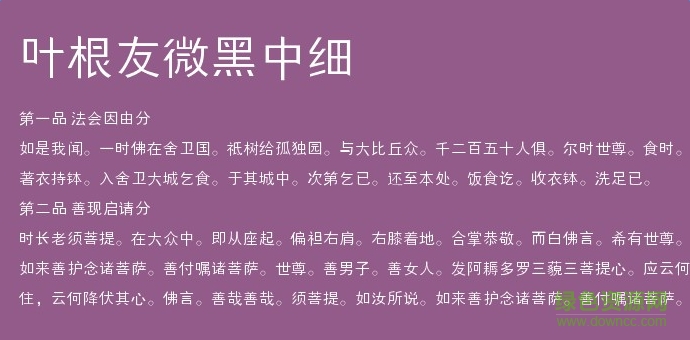
葉根友微黑中細(xì)體
葉根友微黑中細(xì)字體是一款正式簡(jiǎn)約風(fēng)格字體軟件,微黑中細(xì)體是微黑系列中比較熱門(mén)的一款字體,字體細(xì)膩行如流水,整體工整得體大方,適用于各大正文文章的書(shū)寫(xiě),還有更多好看字體歡迎來(lái)綠色資源網(wǎng)下載體驗(yàn)!
葉根友微黑中細(xì)是一款正規(guī)的黑體類(lèi)型的印刷體,整個(gè)字體輕松活潑而有時(shí)代鮮明的特征,整個(gè)筆畫(huà)橫度微斜切,干凈而大氣,簡(jiǎn)約是這款字體的主要特色。每個(gè)筆畫(huà)15度斜角的設(shè)計(jì),使整個(gè)字型看起來(lái)更具時(shí)尚大氣,在應(yīng)用于內(nèi)文、標(biāo)題等都是不錯(cuò)的選擇,葉根友微黑中細(xì)從設(shè)計(jì)到制作歷時(shí)數(shù)年,工程量是普通手寫(xiě)字體的數(shù)倍,每個(gè)筆畫(huà)和結(jié)構(gòu)架次都需要經(jīng)過(guò)精心布局,以求好的效果呈現(xiàn)給用戶(hù)。
葉根友微黑中細(xì)字體
經(jīng)小編測(cè)試使用,在電腦端打字聊天受到非常多書(shū)友們的贊美,這款字體非常好看,文雅性十足,拿來(lái)裝逼再合適不過(guò)了!